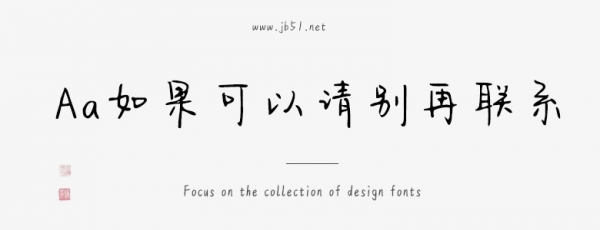
Aa如果可以請(qǐng)別再聯(lián)系是Aa字庫推出的藝術(shù)字體,字體筆觸略細(xì),書寫流暢,具有很好的視覺感,適合應(yīng)用于藝術(shù)設(shè)計(jì)、平面宣傳設(shè)計(jì)、網(wǎng)頁設(shè)計(jì),書法字帖等領(lǐng)域,歡迎需要的朋友下載使用。